Unduh gratis 40 font bulat keren untuk membuat angka, huruf, dan simbol dalam lingkaran.
Download Font Bulat Huruf dan Angka
Berikut kumpulan font bulat Dafont dan FontSpace yang keren dan gratis.
Font Bulat 18 Holes BRK
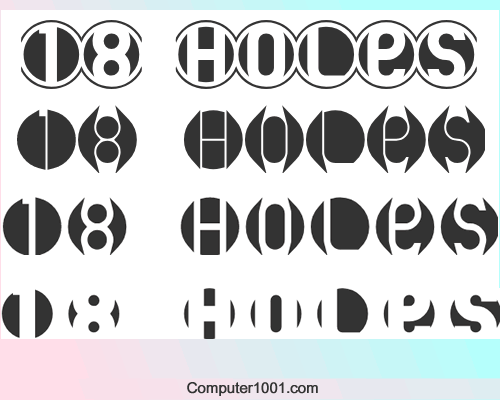
Font ini memiliki 6 bentuk yang unik. Cocok untuk desain poster.
Font Bulat 2Peas Crazy Pooch
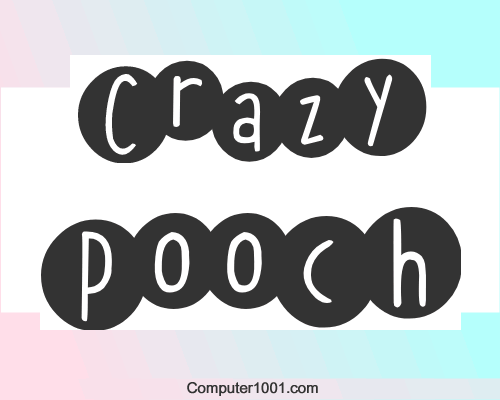
Font gaya tulisan tangan yang lucu. Terdiri dari angka, huruf kecil, dan huruf besar yang posisinya tinggi rendah.
Font Bulat Action Is: The Sequel
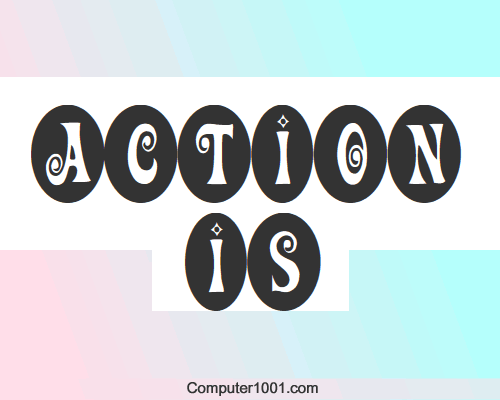
Beberapa karakter pada font Action Is memiliki ujung yang melingkar cantik.
Font Bulat Aylmer
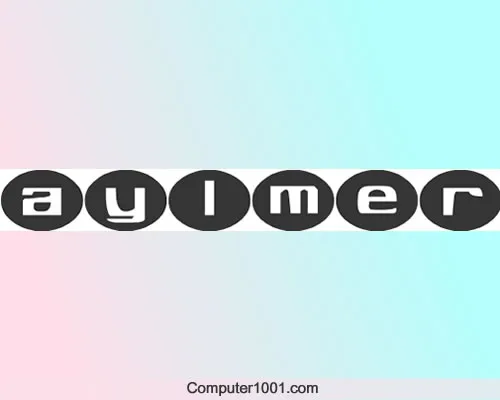
Font Huruf Bulat Kapital Bowl O Rama
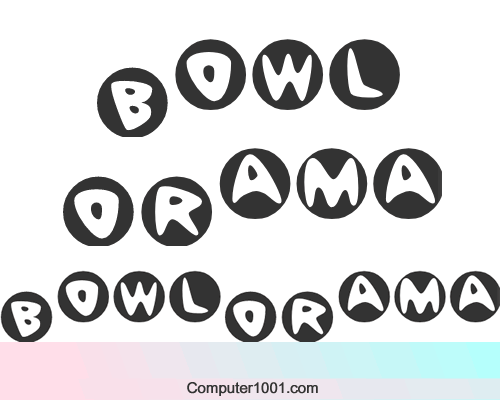
Walaupun tampilannya sama-sama huruf kapital, namun huruf kecilnya memiliki letak yang tinggi daripada huruf besar. Jadi, sangat bagus bila digabungkan untuk mendapatkan tampilan yang keren.
Juga ada tanda baca, tanda hubung, dan angka 0 – 9 yang posisinya tinggi rendah.
Font Bulat Circulate (BRK)
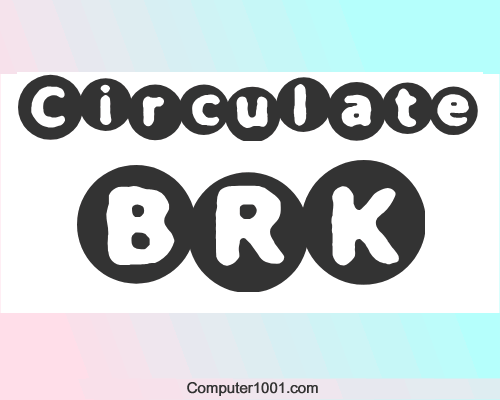
Font Bulat CoNcAdEnAdo St
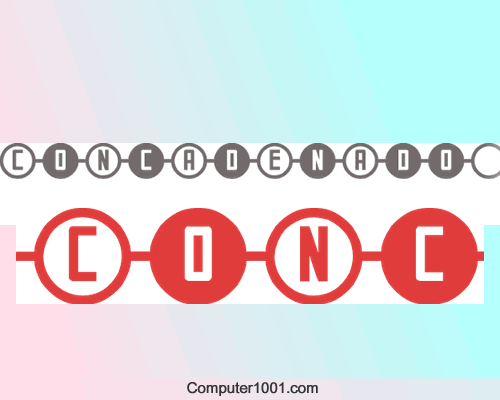
Angka dan huruf besar font ini berada dalam bingkai lingkaran. Sedangkan huruf kecilnya memiliki background solid.
Setiap karakter memiliki garis hubung di kiri kanan.
Font Bulat D3 Mochism
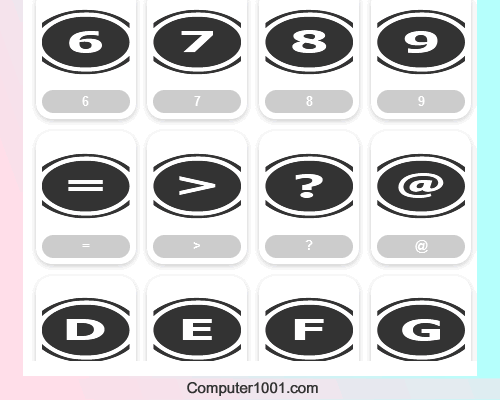
Semua karakter pada font ini berada dalam lingkaran dengan background dan hiasan garis melingkung pada atas dan bawah karakter.
Font Bulat Decorina
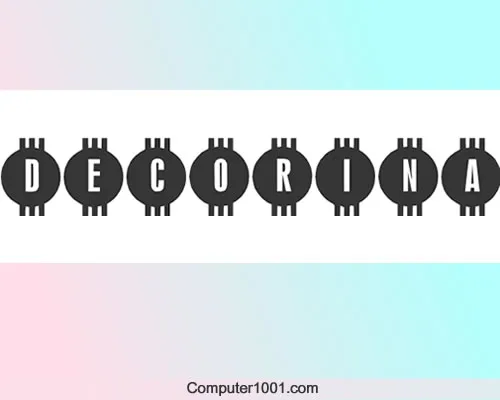
EightBaller Font
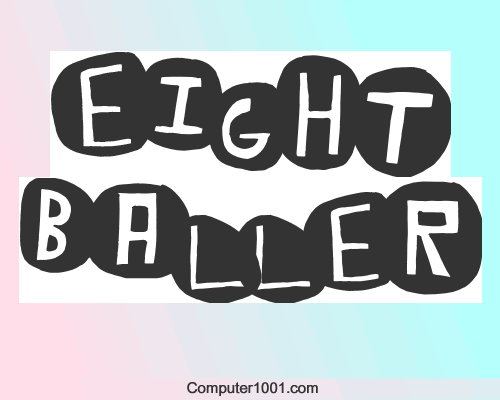
Font EightBaller mirip seperti coretan tangan yang tidak beraturan dan bentuknya besar kecil.
Font Bulat Everything Unique
Font Display Bulat Fire Within
Font display bulat dengan desain yang unik. Ada gambar bunga, mata, dan telapak kaki.
Font Bulat GaraNitials
Jambo Round Font Huruf Kapital
Font Roda Ban JLR Li’l Bit Tires
Font Bulat KBCaterpillar
Font Bulat KBPopTheBubbly
Lingkaran pada font ini seperti dibuat dengan spidol, sehingga menghasilkan garis yang tebal.
Font Bulat Kapital KG Counting Stars
Gunakan huruf kecil untuk mendapatkan huruf kapital dengan hiasan bintang pada kiri dan kanan karakter.
Font Bulat KG Wake Me Up
Font Huruf Bulat Kapital KR Sami’s Mark
Font Huruf Dalam Lingkaran Letters in Circles
Font ini ada 2 gaya, yaitu font dengan outline lingkaran dan font dengan background saja.
Magic Marbles Font Bulat Tebal
Font ini memiliki 2 gaya, yaitu reguler dan italic. Huruf besar dan huruf aksen pada gaya reguler memiliki bentuk miring ke kiri.
Gunakan huruf kecil untuk membuat huruf besar yang miring ke kanan.
Font Bulat Milit
Font Bulat Mister
Lingkaran hitam tebal pada karakter terpotong di kiri kanan. Untuk membuat lingkaran bulat seperti contoh pada gambar, maka tempatkan tulisan dalam tanda kurung siku […].
Font Bulat Molecular
Huruf besar font ini berbentuk seperti molekul dengan 2 garis penghubung. Sedangkan huruf kecil berupa lingkaran biasa untuk digunakan sebagai penutup pada akhir tulisan.
Demikian juga dengan angkanya. Untuk penutupnya, ketikkan huruf aksen atau kombinasi tombol keyboard keypad numerik.
Contoh: huruf aksen È atau shortcut tombol ALT + 0200 akan menghasilkan angka nol dalam lingkaran. Lihat daftar lengkapnya pada character map di bagian Latin-1 Supplement.
Font Bulat NavyBlues